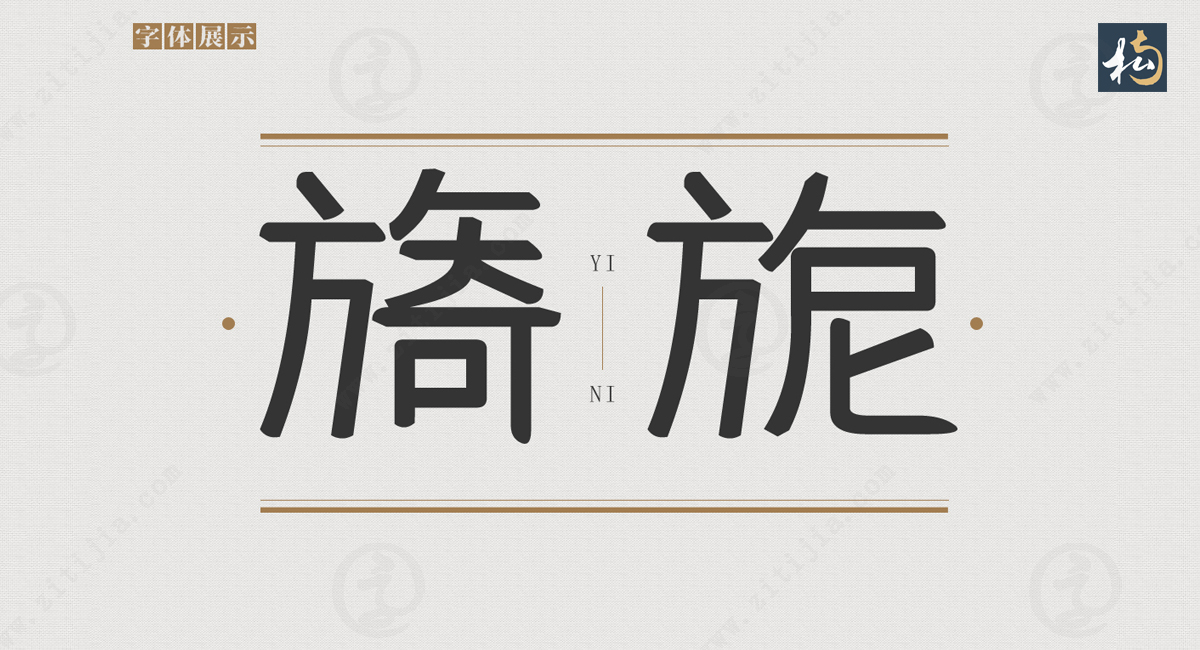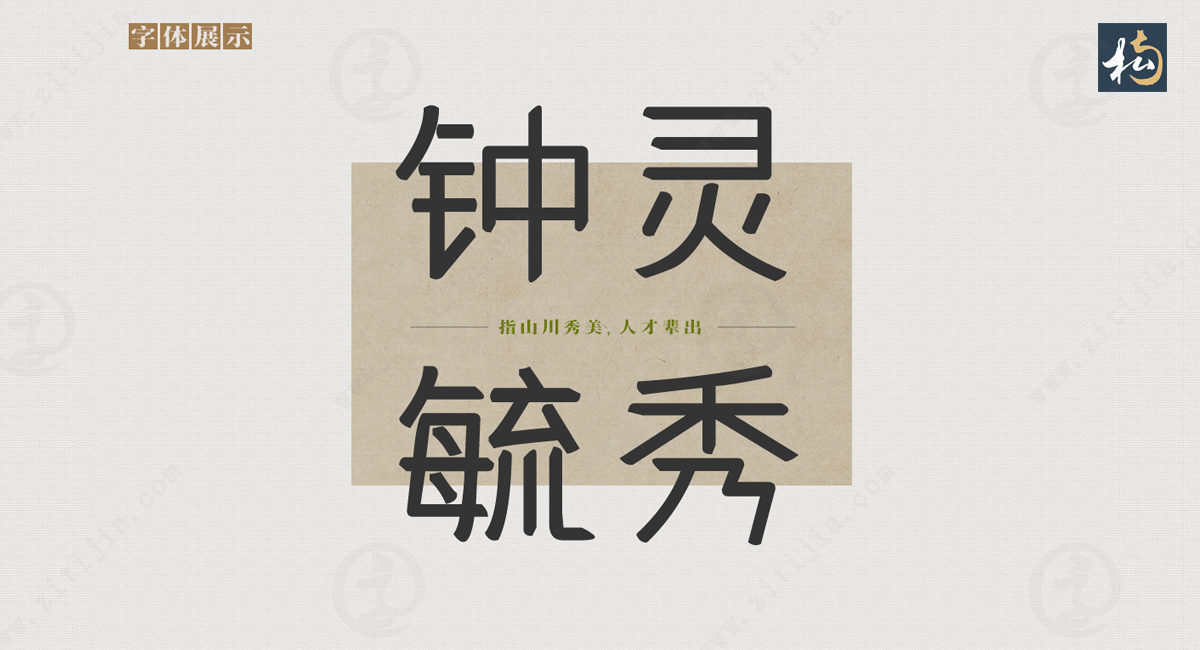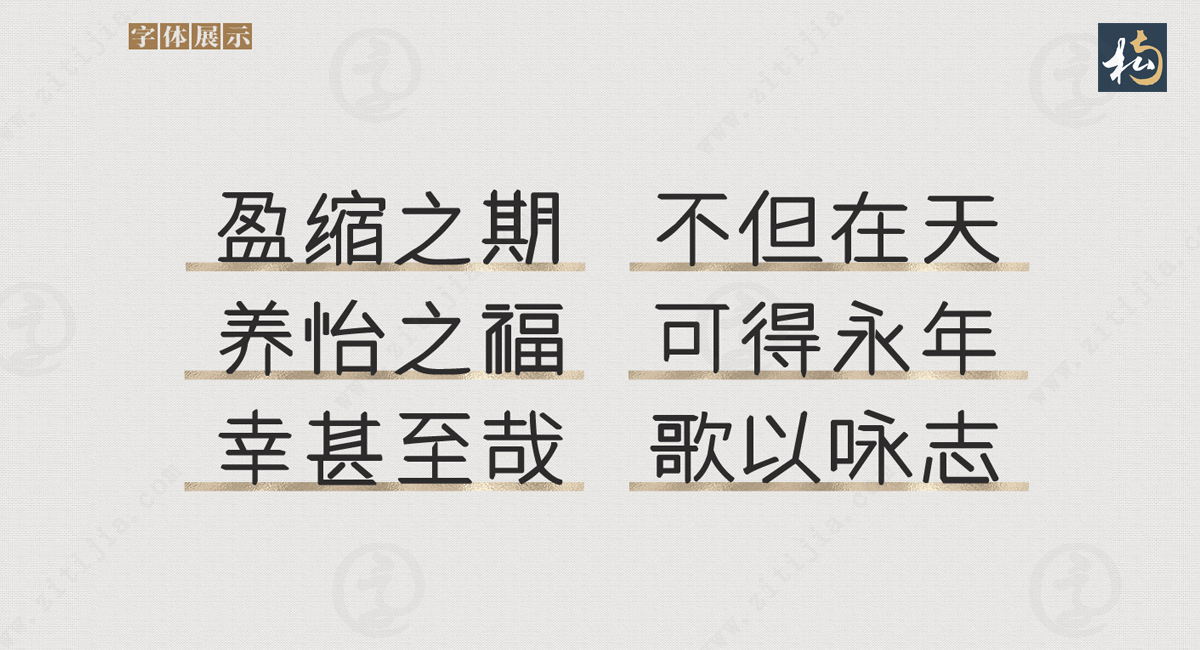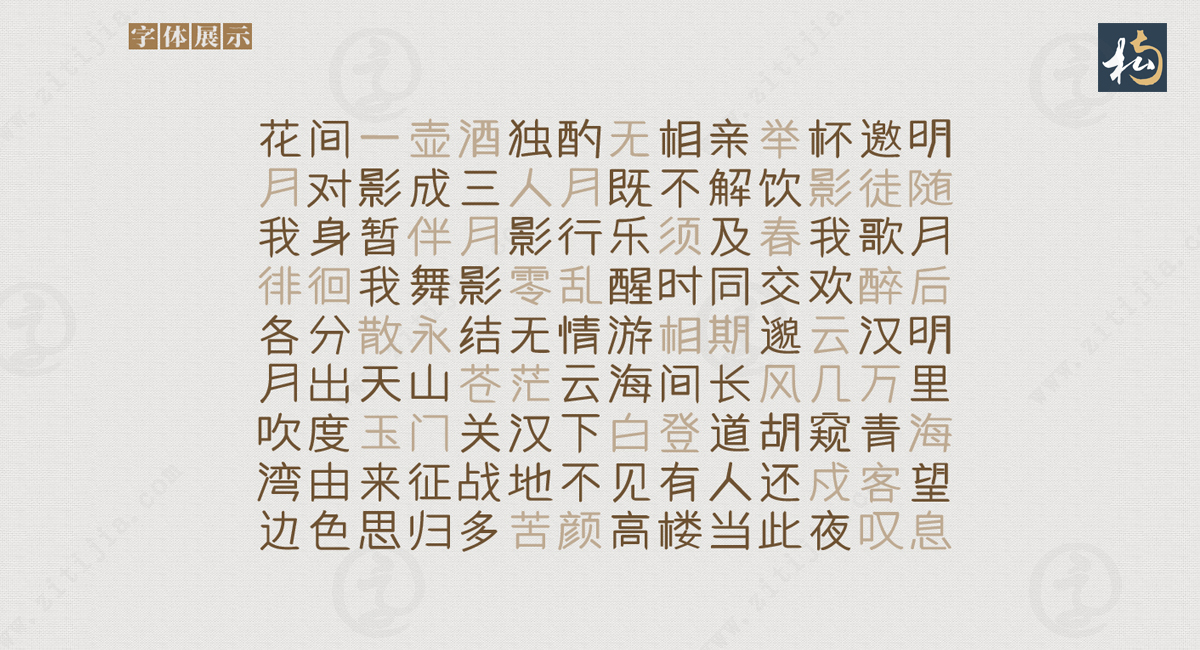
一款端正美观的艺术字体,南构宜宋颜值字体欣赏
在当今的设计领域中,字体不仅仅是一种文字的表达工具,更是一种艺术形式的展示。南构宜宋颜值就是一款非常不错的艺术字体,由南构字库倾力打造。它以其端正美观的外观、横平竖直的笔画和现代感十足的设计风格,成为了报纸、杂志和书籍中常用的字体之一。同时,它也非常适合海报、个性促进品牌标志设计和字体设计等环境的使用。
南构宜宋颜值字体的最大特点之一就是其端正美观的外观。每一个字母和字符都经过精心设计,保持了字形的规整和平衡。无论是大标题还是小文字,南构宜宋颜值都能够展现出其独特的美感。这种美感不仅仅体现在字形的外观上,还体现在字体的整体布局和排版上。使用南构宜宋颜值字体,可以让文字更加清晰、优雅,增加设计作品的整体品质。
除了端正美观的外观,南构宜宋颜值字体的笔画横平竖直,使得每个字母和字符都显得更加工整。这种规整的笔画不仅让文字看起来更加舒适,还增加了字体的可读性。在报纸、杂志和书籍中,文字的可读性是非常重要的,而南构宜宋颜值字体能够满足这一需求。无论是长篇文章还是短小标题,南构宜宋颜值字体都能够保持清晰的笔画,使读者更加轻松地阅读和理解内容。
南构宜宋颜值字体的现代感也是其受欢迎的原因之一。在当代设计中,现代感是一个非常重要的元素。南构宜宋颜值字体通过其简洁而时尚的设计风格,展现出现代感十足的特点。这使得它非常适合用于海报、个性促进品牌标志设计和字体设计等环境中。使用南构宜宋颜值字体,可以让设计作品更加与时俱进,吸引观众的目光,提升品牌形象和宣传效果。
总之,南构宜宋颜值是一款非常不错的艺术字体,具有端正美观、笔画横平竖直和现代感强烈的特点。它适应于报纸、杂志和书籍中的常用字体,同时也非常适合海报、个性促进品牌标志设计和字体设计等环境的使用。如果你是一个喜欢追求艺术和时尚的设计师,那么南构宜宋颜值字体将是你的不二选择。欢迎喜欢的朋友前来字体家下载使用,让你的设计作品更加出色!